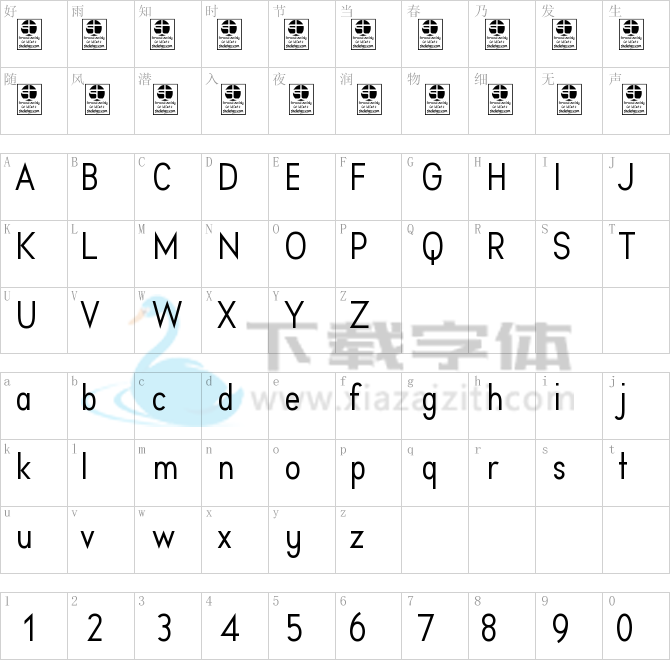
Aprikas Regular Demo.otf字体下载,这款字体结构工整、笔画清晰,兼顾美观与易读性,适用于标题、正文、海报、包装、LOGO 等多种场景。字形优雅稳定,风格百搭耐看,适配日常排版与创意设计,让文字呈现更舒适、更具质感。Aprikas Regular Demo.otf字体下载一笔一画,皆是细节,以均衡的比例、流畅的线条打造舒适视觉体验,字形端正大气,风格简约现代。无论是商业设计、品牌宣传还是日常排版,都能轻松驾驭,让文字更有格调与力量。Aprikas Regular Demo.otf字体下载字体下载。
• 字体名称:Aprikas Regular Demo
• 字体全名:Aprikas Regular Demo